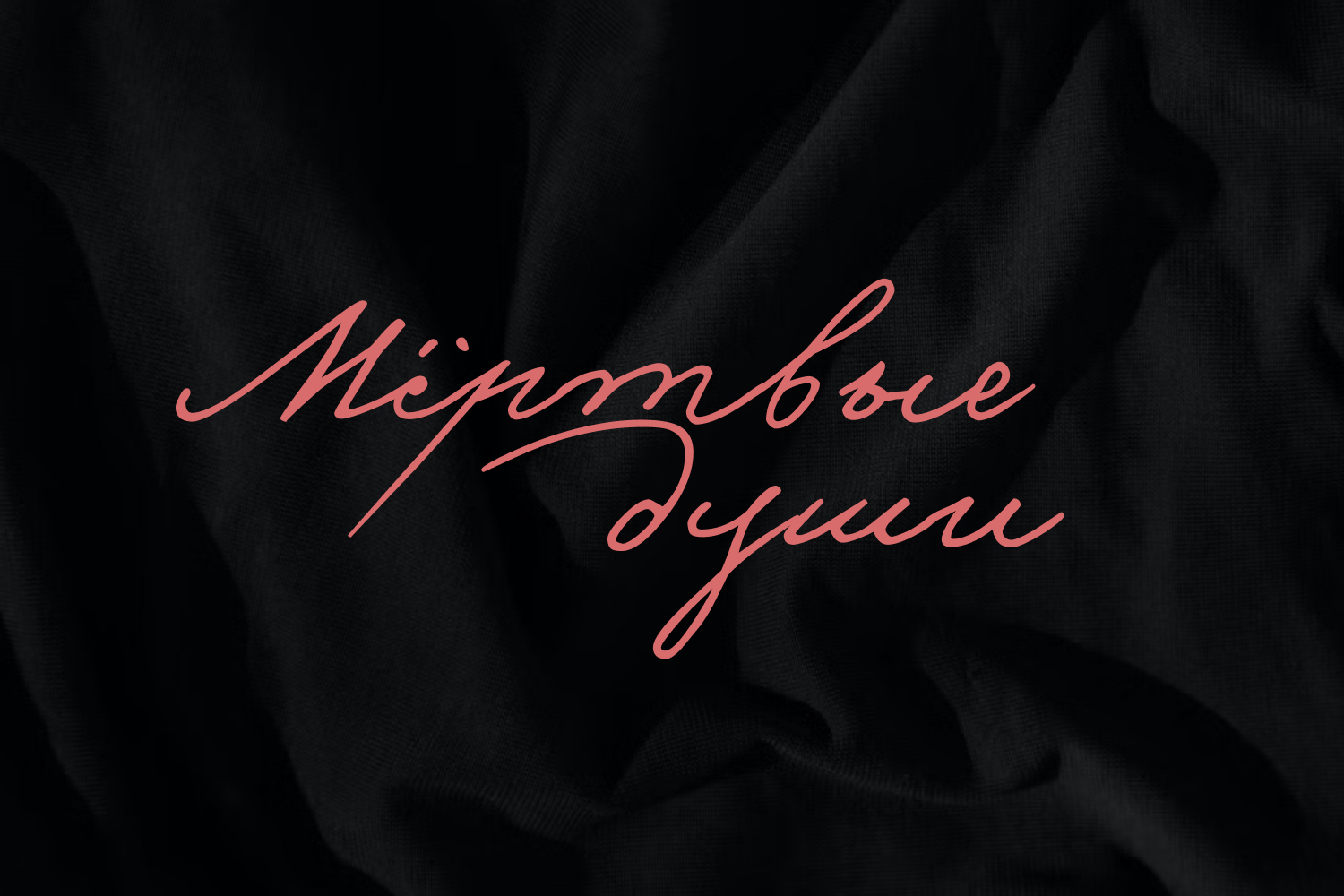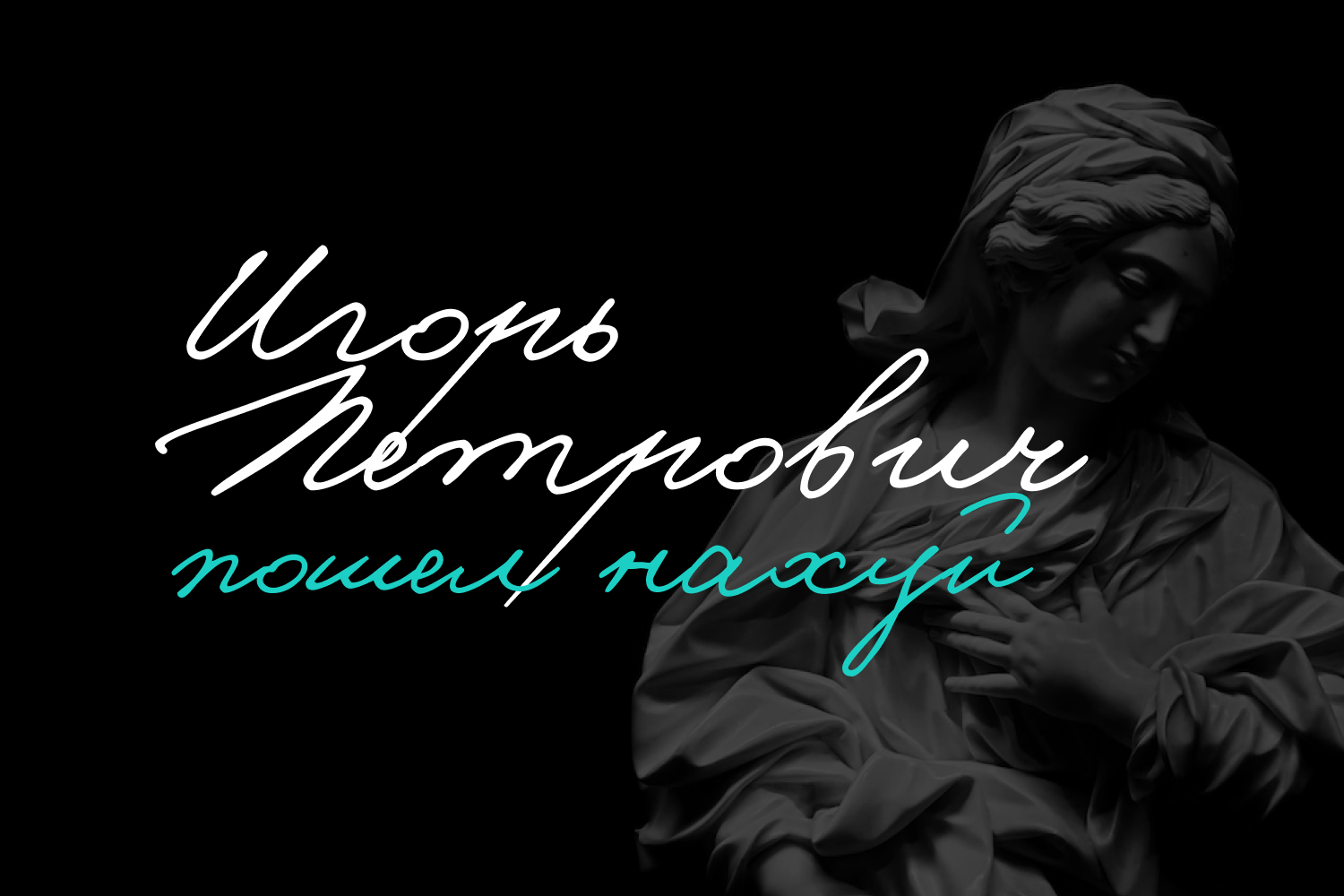
Шрифт gogol
Да иди ты *** Идеальный шрифт, чтобы послать начальника или плохого заказчика. Этот шрифт, настолько красив, что любое некрасивое слово станет прекрасным.
Им же можно писать стихи любимому человеку. Всем же известно: «От любви до ненависти – один шрифт»
Шрифт Gogol подготовлен к 200-летию со дня рождения великого русского писателя.
Автор: студия Paratype